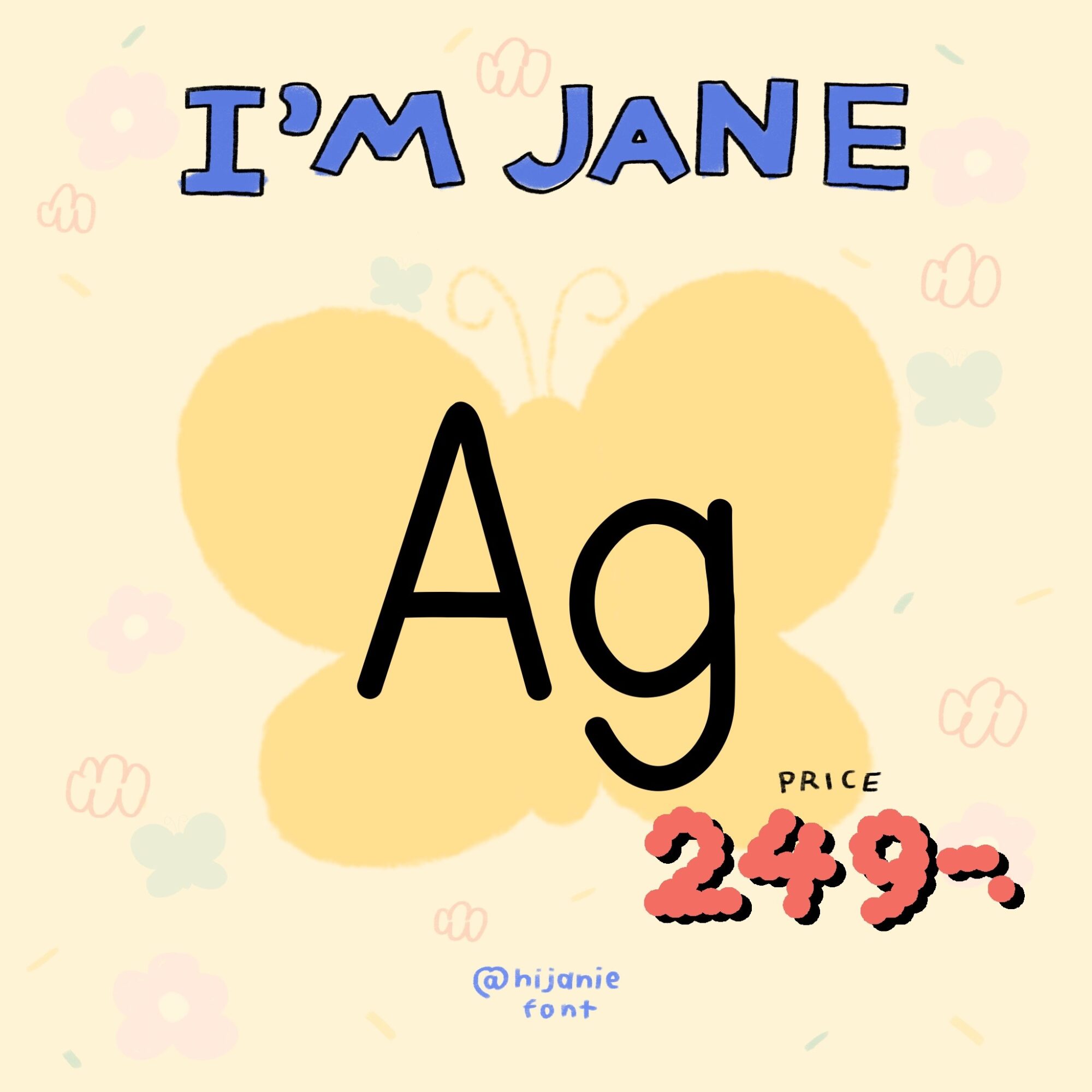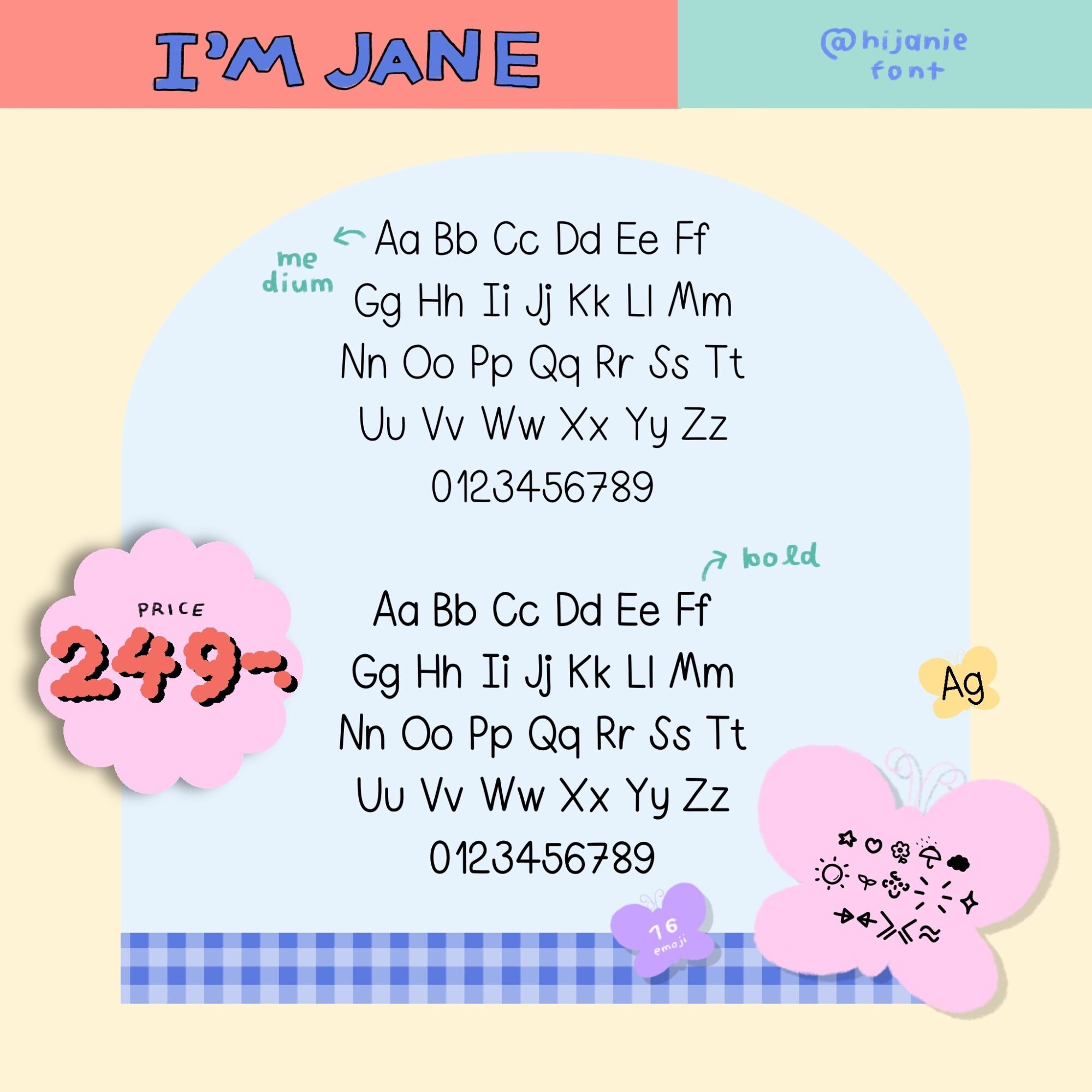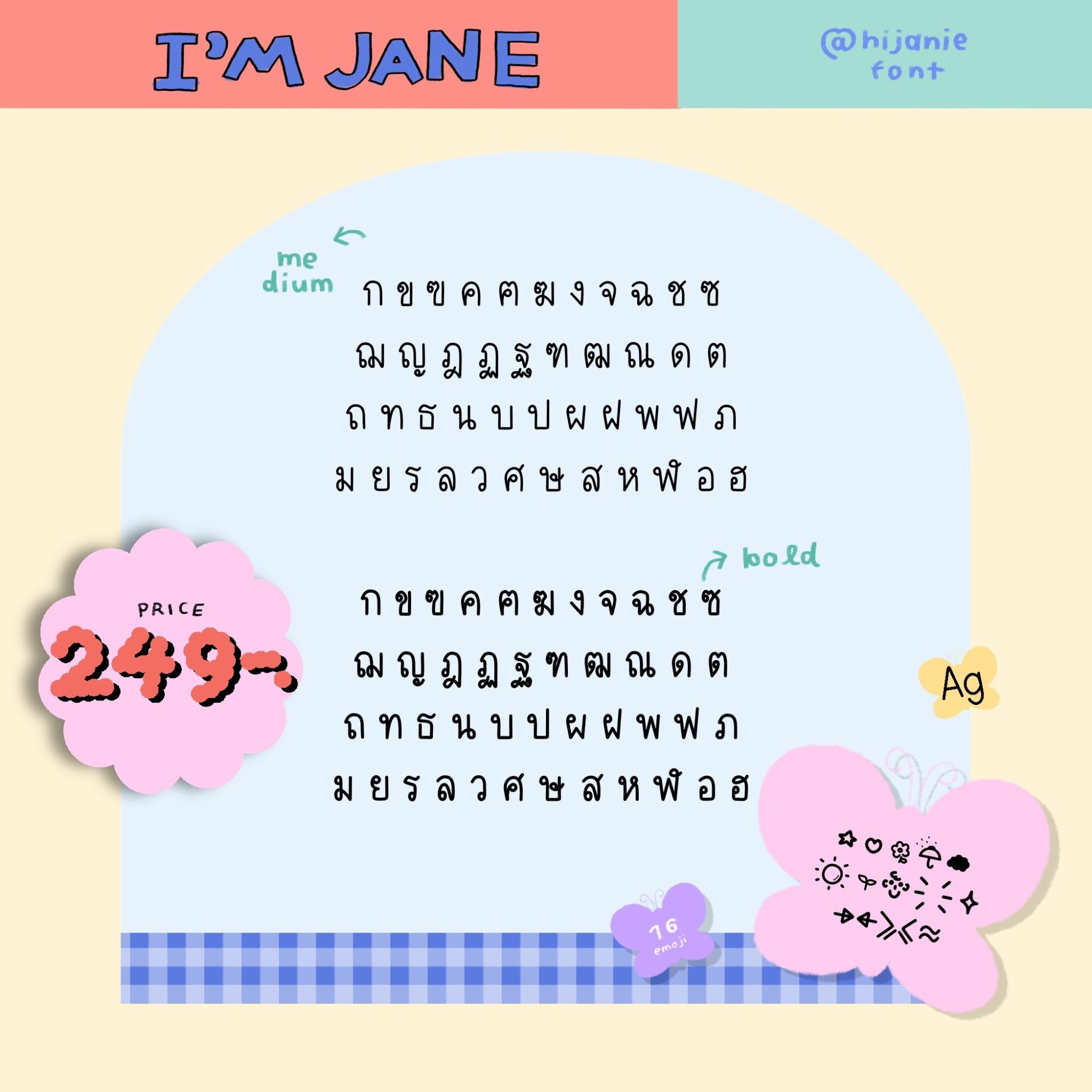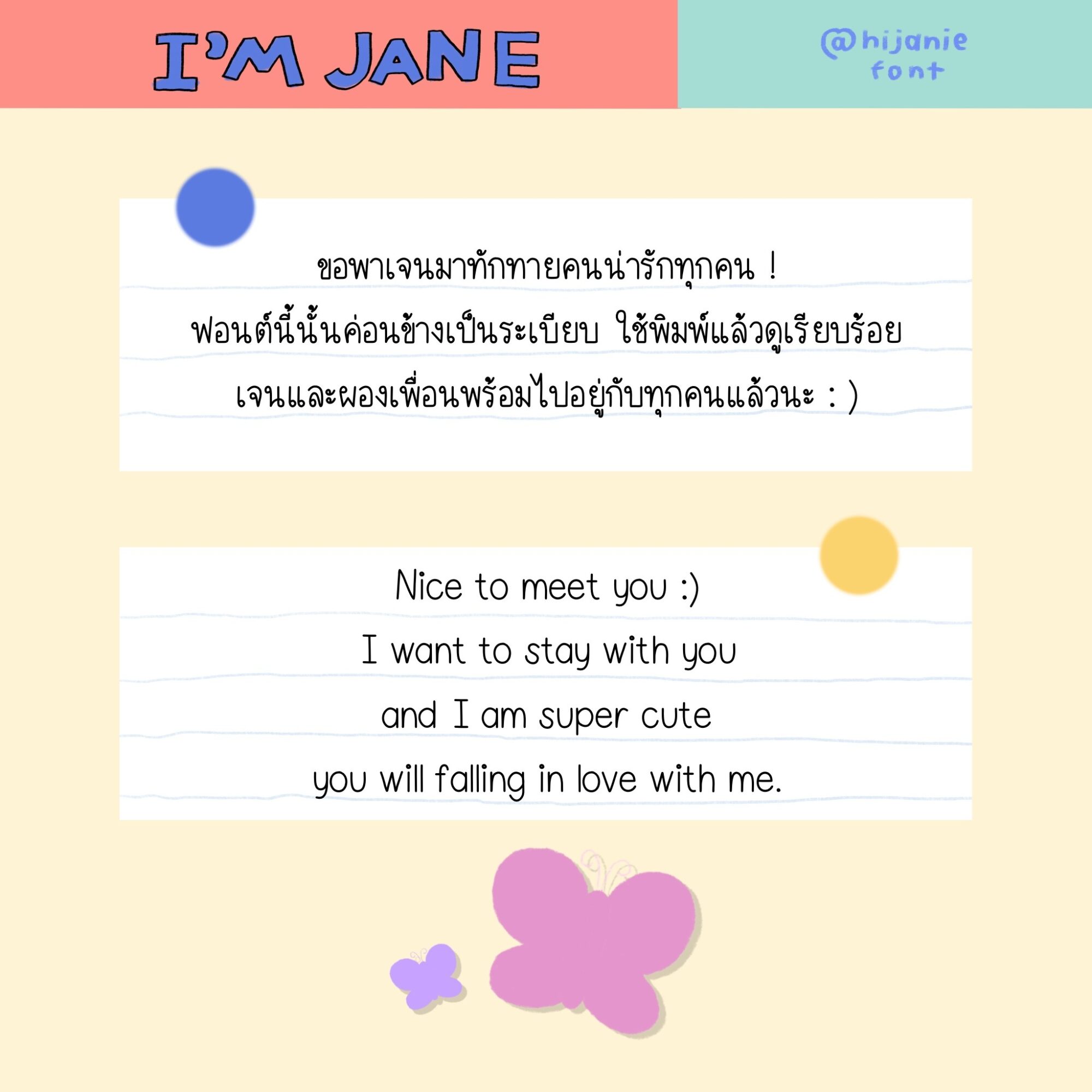
font : Im Jane
🤙🏽— font : Im Jane
・สำหรับใช้พิมพ์งานต่าง ๆ หรือประกอบงานกราฟิก
・ฟอนต์ขนาด medium
・ฟอนต์ขนาด bold
🤙🏽— font : Im Jane
・ Intended for document printing and graphic design purposes
・ font Im Jane in medium size
・ font Im Jane in bold size